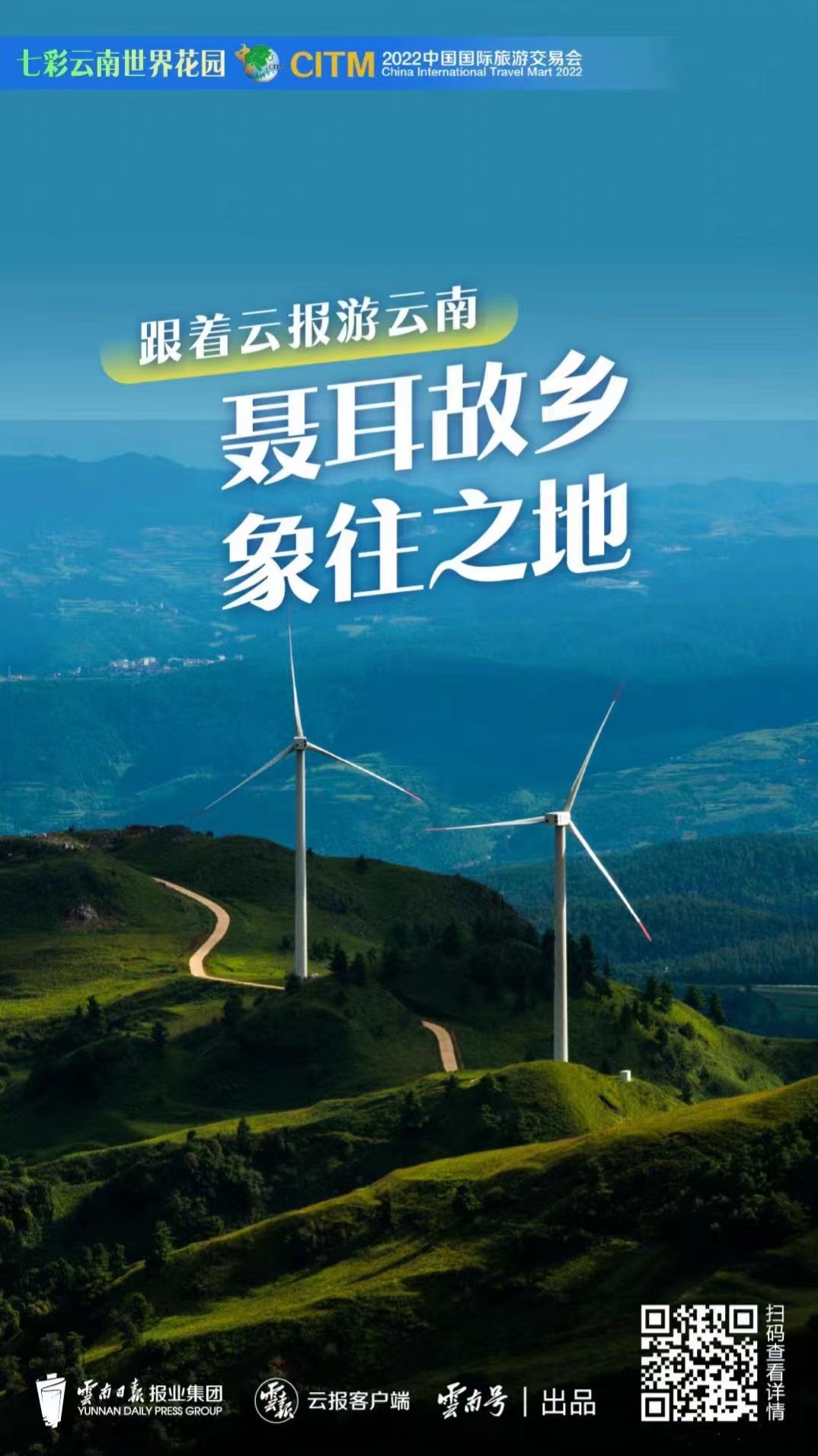
方正蕴黑家族
刘晶
方正蕴黑是一款基于黑体的创意字体,这款字浑厚朴拙,重心平稳,端庄大方,集刚正硬朗的力度美与温润柔和的曲线美于一体。笔画连接处适当的断笔处理,使字体空间变得更加透气活泼,充满更多的层次和变化。方正蕴黑粗体雄健有力,细体雅致简约。适用标题 、产品包装、广告、出版物、品牌等应用环境。